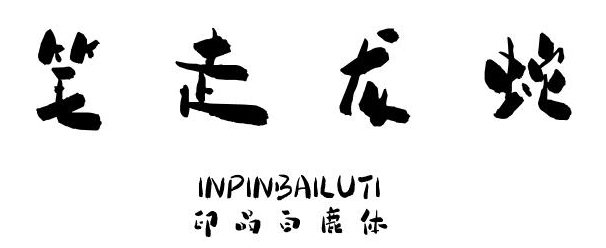
印品白鹿體是印品系列字體中最獨具一格的義啟字體,整體上偏向于毛筆書法的厚重與濃墨,造型上兼具手寫體的隨性和優(yōu)雅,風格多樣十分好看,喜歡的朋友就來綠色資源網(wǎng)試試吧!
白鹿體的靈感來源于鹿,將鹿的形態(tài)特質(zhì)運用到書法當中,猶如一只只小鹿躍然紙上,奇趣橫生,借此呼吁大家要保護生態(tài)保護動物。
印品白鹿體以筆走龍蛇為特色,更顯飄揚不羈,讓文字綻放獨有的藝術光彩,給大家?guī)砀由暇€悅目的特色體驗,讓你平面設計、包裝設計更加出色!